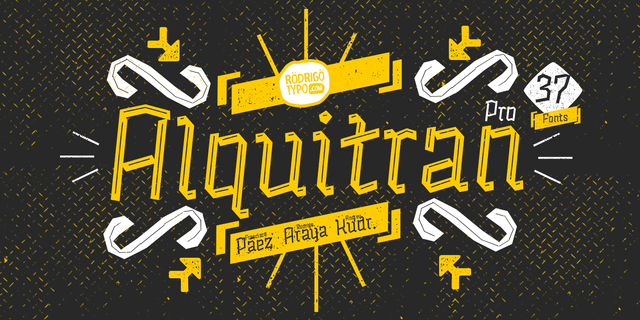
Шрифт по мотивам pixaçao или pichaçao — особый жанр граффити, возникший в Сан-Паулу в 1980-е годы, хотя в 1960-е годы уже существовали подобные граффити против военной диктатуры, в контексте профсоюзной борьбы. Это были протестные теги, нарисованные смолой (порт. piche — смола) на зданиях на большой высоте. В шрифте Alquitran (исп. Alquitrán — деготь) этот уникальный вид леттеринга переработан в несколько более формальном стиле, добавлены разные начертания с поддержкой многих языков, включая кириллицу, и декоративные орнаменты. Шрифт разработали Родриго Арая Салас, Франциско Паез и Андрей Кудрявцев в 2018 году.